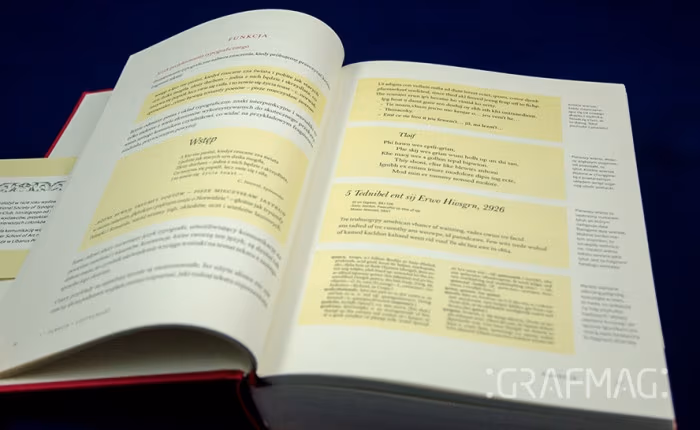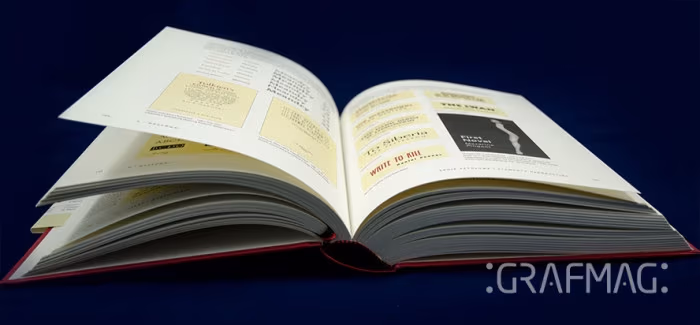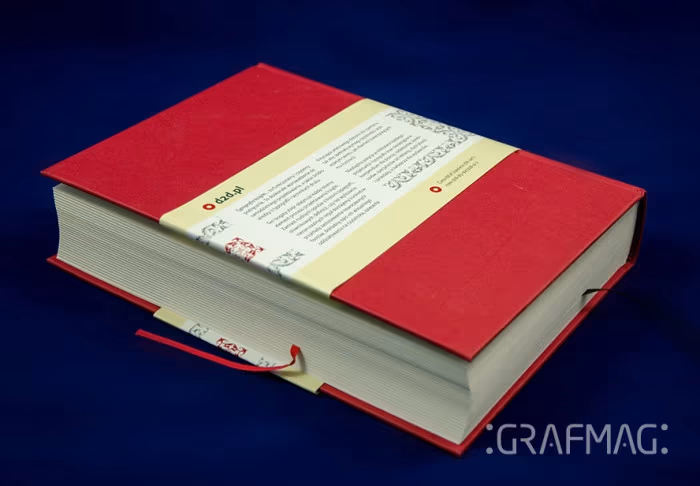
Każdy, kto chce zajmować się składem książki powinien najpierw sam przeczytać parę wartościowych publikacji poświęconych typografii. Jedną z takich obowiązkowych pozycji jest według mnie „Typografia książki. Podręcznik projektanta” wydana przez wydawnictwo d2d.pl.
Autorzy publikacji są autorytetami w tej dziedzinie, zawodowo związanymi z zagadnieniami składu i wydawania książki. Michael Mitchell w 1976 roku założył własne wydawnictwo Libanus Press, oprócz tego jest członkiem dwóch prestiżowych stowarzyszeń – International Society of Typographic Designers oraz Double Crow Club (zrzesza wydawców, drukarzy, projektantów). Susan Wightman jest natomiast projektantem we wspomnianym wyżej wydawnictwie.
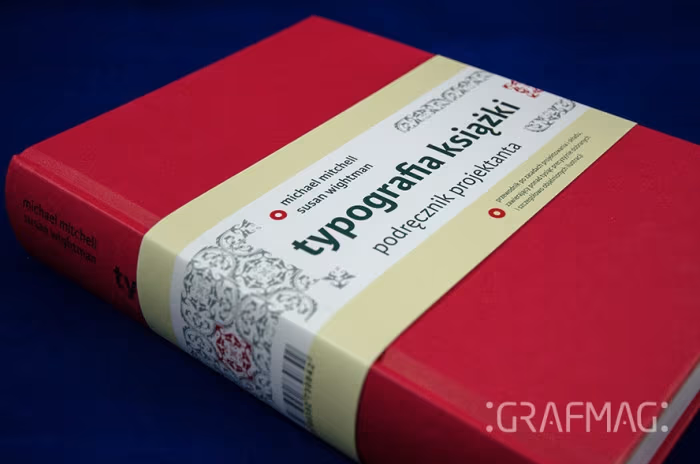
Jak zaprojektowano Podręcznik projektanta?
Jako że książka mówi o projektowaniu książki, przyjrzyjmy się, jak ona sama została zaprojektowana. Książka robi wrażenie już na pierwszy rzut oka. Potężna, zawiera ponad 400 stron tekstu wydrukowanych na dobrym papierze, oprawionych w twardą okładkę. Przez to nie jest może zbyt poręczna do czytania, nie zabierzemy jej do torebki, ale to dobrze – jej waga i gabaryty wymuszają poniekąd czytanie w jednym miejscu, a więc w skupieniu. Okładka jest bardzo oszczędna w formie, elegancka – cała czerwona, pozbawiona jakiejkolwiek grafiki, tylko na grzbiecie widnieje tytuł oraz autorzy. Do tego nieprzegadana banderola dobrze kontrastująca z okładką.
Treść jest zorganizowana w bardzo przejrzysty i czytelny sposób, ułatwiający czytelnikowi szybkie znalezienie oraz przyswojenie informacji. Całość podzielono na rozdziały – każdy, zgodnie z zasadami składu książki, zaczyna się na osobnej stronie recto (strona po prawej), gdzie dodatkowo wypisano podrozdziały. Zastosowano różne, stopniowane wielkością formaty nagłówka, wyróżnione tym samym kolorem. Dodatkowo, na marginesach umieszczono poruszane w poszczególnych akapitach pojęcia, zagadnienia. W składzie tekstu zachowano szerokie marginesy, dość sporą interlinię, co ułatwia czytanie. Liczne przykłady wyróżniono na jasnożółtym tle. Jednym słowem – książka całą sobą obrazuje głoszone w niej zasady dotyczące prawidłowego składu książki. Jedyna kwestia, która nie przypadła mi do gustu, to zastosowana kolorystyka – blady odcień żółtego i dziwna czerwień zmieszana z magentą użyta w nagłówkach.
Treść książki
Książka zawiera aż szesnaście rozdziałów. Wszystkie tematy są omówione bardzo dokładnie, zilustrowane dodatkowo precyzyjnie dobranymi i szczegółowo objaśnionymi obrazkami.
Rozdziały o składzie tekstu
We wstępie przytoczono podstawowe terminy związane z budową i składem książki. Następnie, pierwsze dziesięć rozdziałów poświęcono omówieniu składu i organizacji samego tekstu. Na początku autorzy analizują zależności pomiędzy stopniem pisma, światłem, interlinią a czytelnością tekstu. Czytelnością rozumianą nie tylko jako rozpoznawalność poszczególnych znaków, ale przede wszystkim jako łatwość, z jaką czytamy tekst – a to zależy od tego w jaki sposób został on złożony. Poznamy formaty wydawnicze oraz sposoby organizacji kolumny tekstu – rozmieszczenie na stronie, układ, wyrównanie, odpowiednia wielkość marginesów. Dowiemy się, co to jest całostka, jak powinien być złożony pierwszy po tytule akapit, a także jaka jest optymalna liczba słów w linijce.
Trzeci rozdział jest w całości poświęcony krojom pisma – szczegółowo omówiono cechy krojów, a więc wielkość, wysokość x, szerokość, światło, przytaczając jednocześnie przykłady zależności pomiędzy poszczególnymi krojami pisma a szerokością druku. Nie zabrakło także podrozdziału o rodzinach krojów (kroje tytułowe, akcydensowe, odmiany pochyłe) czy kategoriach pism drukarskich (pisma szeryfowe, bezszeryfowe i akcydensowe). Na uwagę zasługuje część o wyborze kroju dziełowego. Autorzy podkreślają jak ważne jest dopasowanie do treści książki odpowiedniego kroju pisma i składu.
W kolejnym rozdziale bardzo zaciekawił mnie temat odpowiedniego ustawienia odstępu międzywyrazowego, który, zwłaszcza w przypadku justowania, wydawał mi się dość problematyczny w takich programach jak Indesign (zawsze pojawiały się nieodpowiednie „dziury” w tekście lub zbytnie zagęszczenie słów – teraz już wiem, jak tego uniknąć!). Dodatkowo, znajduje się tu podrozdział o ręcznym korygowaniu składu (nie spotkałam się z inną pozycją poświęcającą uwagę tej kwestii) – dowiemy się, na czym polega naciąganie tekstu justowanego i jak prawidłowo organizować tekst wyrównany lewostronnie (wbrew pozorom nie jest to aż taki prosty sposób składu – nie występuję tu problem odstępów międzywyrazowych, ale za to „postrzępiona” krawędź też powinna być zorganizowana w „naturalny” sposób).
Dalej omówione zostały nagłówki – ich spójna i prawidłowa gradacja oraz dobranie odpowiedniego kroju pisma. Bardzo cenne są wskazówki dotyczące organizacji rozdziałów w książce: jak rozmieszczać tytuły rozdziałów, gdzie umieszczać motta, czy stosować inicjał wpuszczony czy podniesiony, co to jest kolumna spuszczona, winieta czy bordiura.
Rozdział szósty dotyczy organizacji stron tytułowych, materiałów wprowadzających i uzupełniających w książkach (a więc m.in. strony redakcyjnej, spisu treści, przedmowy, wstępu, aneksu, spisu ilustracji). Poznamy też takie pojęcia jak pagina bieżąca i żywa oraz rodzaje przypisów.
Na pewno wiele tych zagadnień było omówionych w innych książkach poświęconych typografii. Jednak zazwyczaj ograniczano się w nich do krótkiego wyjaśnienia w jednym akapicie. Tutaj natomiast każdy element jest przedstawiony na paru stronach, zobrazowany różnymi przykładami, które w spokoju możemy przeanalizować i zobaczyć, jak drobne różnice wpływają na czytelność lub wygląd złożonego tekstu.
W książce znajdziemy także bardzo przydatny rozdział poświęcony znakom przystankowym czy, rzadko spotykane w innych książkach, omówienie cyfr (np. co to są cyfry nautyczne). Rozdział VIII pomoże nam natomiast opanować trudną sztukę szacowania objętości książki w zależności od liczby znaków na stronie, stopnia pisma czy zastosowanej interlinii.
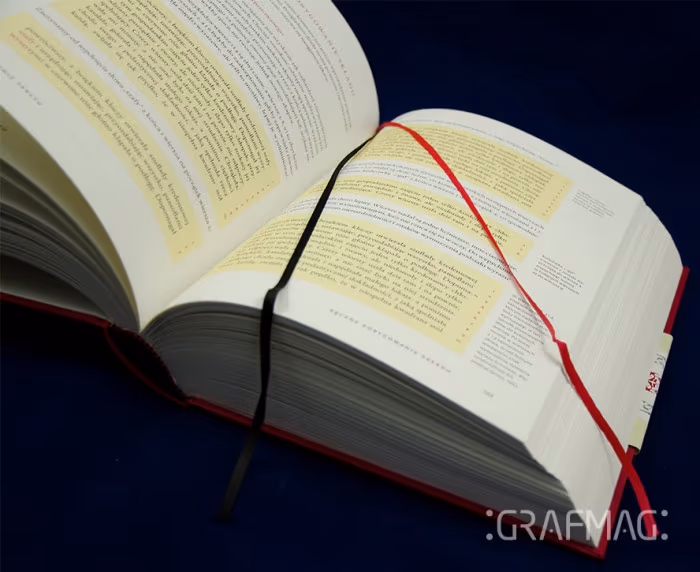
Rozdziały o budowie książki
Ostatnie sześć rozdziałów poświęconych jest raczej na omówienie budowy samej książki, jej elementów. Poruszony jest temat książek ilustrowanych, pracy z ilustracjami, ich rozmieszczania (znowu opatrzone licznymi przydatnymi przykładami) oraz okładki – rodzaje oprawy, komponenty okładki i obwoluty. Bardzo przydatne są zwłaszcza podrozdziały o typografii okładki i obwoluty – prawidłowym rozmieszczaniu tekstu na skrzydełkach obwoluty, grzbiecie, tylnej okładce. Na koniec przedstawiony jest też sam proces produkcyjny książki – zasady redakcji, od korekty do druku i jego nadzoru.
Podsumowanie
Niektórym osobom ta pozycja może wydawać się zbyt długa, a ilość przykładów zbyt duża i zbędna. Na pewno nie jest to książka z serii „skład książki w 24 godziny” ani podręcznik obsługi programu do składu. Ta publikacja zachęca do szczegółowego i badawczego przyjrzenia się anatomii książki, wręcz pewnego rozsmakowania się w jej poszczególnych elementach. Trzeba jednak zaznaczyć, że autorzy skupiają się przede wszystkim na przedstawieniu takich zasad składu, które mają uczynić książkę bardziej czytelną i przyjazną czytelnikowi. Nie znajdziemy więc tu przepisów na nowoczesny czy innowacyjny layout.